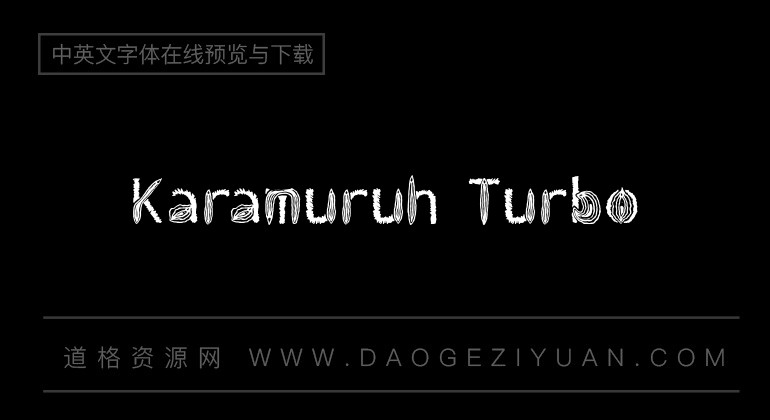
Karamuruh Turbo
Karamuruh Turbo 字体是一款由日本设计师Ryoichi Tsunekawa设计的日本字体,它具有浓重的涩调,是一款极具特色的日本字体。Karamuruh Turbo的字体设计融合了日本传统的调和感,拥有更多的可读性,更加现代化的感觉,以及更大的空间感。它可以用于各种不同的场合,从商业到社交,从娱乐到科技,都可以找到合适的应用。
Karamuruh Turbo是一款非常不错的手写艺术字体,具有很好的视觉感,适合于文化类的宣传设计、商业类品牌的广告和产品包装设计以及个性化文字排版等较多场景。